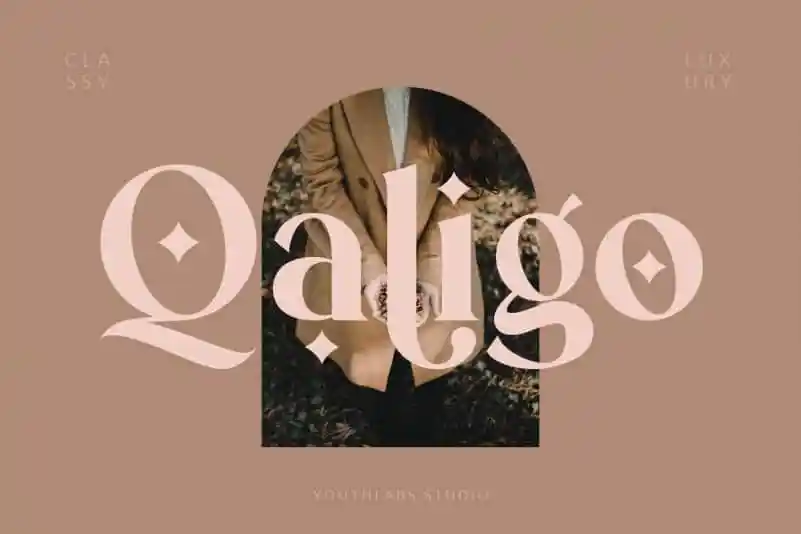
A Qaligo Serif Font é uma criação moderna e clássica, perfeita para projetos visuais variados, desde logos até a criação de marcas. Ela foi desenvolvida pelo designer youthlabs e traz um toque de sofisticação com sua forma luxuosa. Além disso, possui mais detalhes em seu design, o que torna-a ainda mais atrativa e elegante. Com Qaligo Serif Font, você pode criar texturas e linhas com mais precisão e refinamento graças aos seus recursos OpenType avançados. Uma fonte de escrita sofisticada como essa é certamente uma escolha brilhante para quem busca um toque de luxo em suas criações.